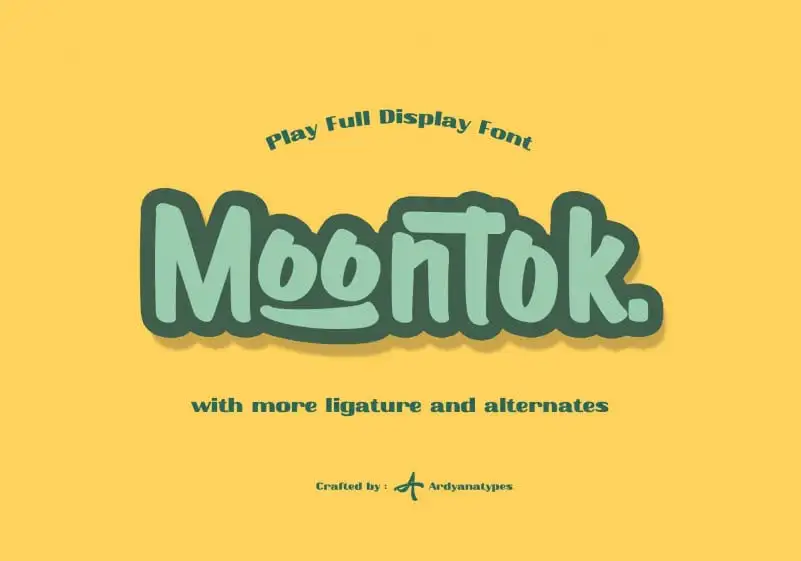
A Moontok Font é uma elegante e moderna seleção de letras para projetos digitais, especialmente adequada para criações de design que precisam de um toque atraente e personalizado. Como mencionado na descrição original, esta fonte foi pensada para adicionar um ar ligeiramente infantil e deslumbrante ao seu próximo projeto. Ela transmite uma sensação de frescor verão e alegria com seus traços suaves e encantadores. A Moontok é perfeita para projetos que requerem uma textura fofa, como nomes de bebês, selos ou até mesmo gráficos infantis. Com essa fonte, o design pode ter um toque leve, fresco e descontraído — ideal para criar experiências visuais que chamam a atenção e criam emoção. Não perca tempo em encontrar a sua nova fonte favorita; A Moontok Font está aqui para dar um novo encanto aos seus projetos de design.